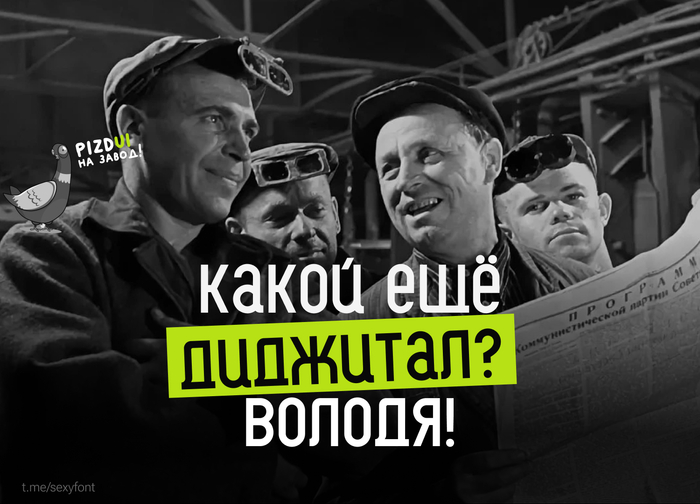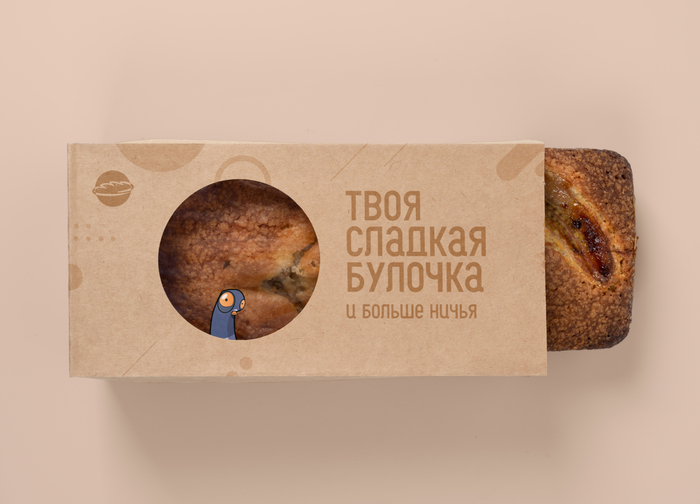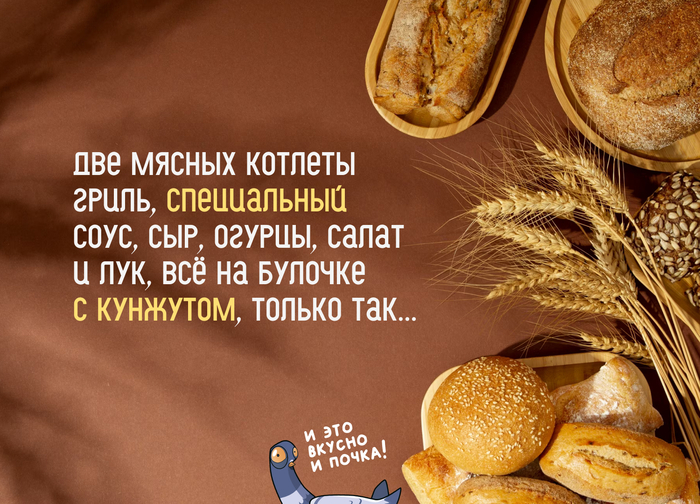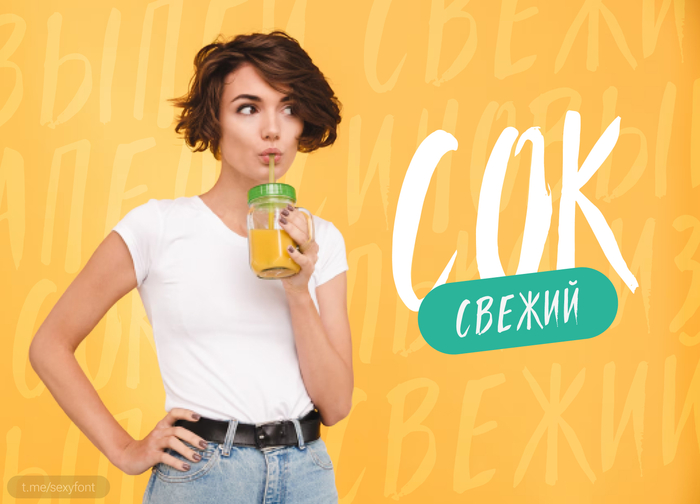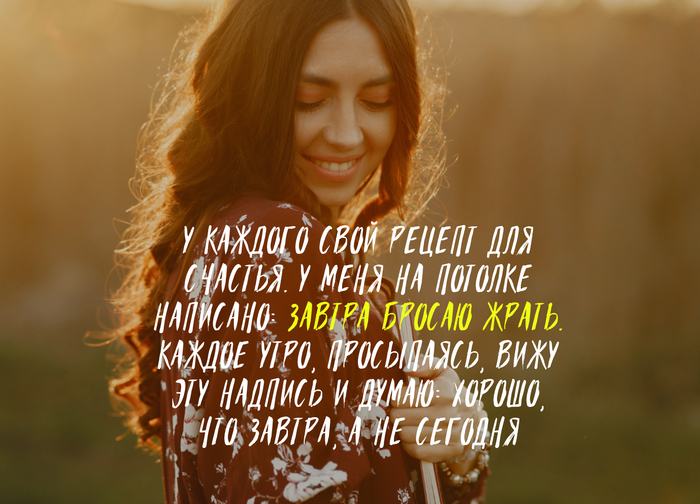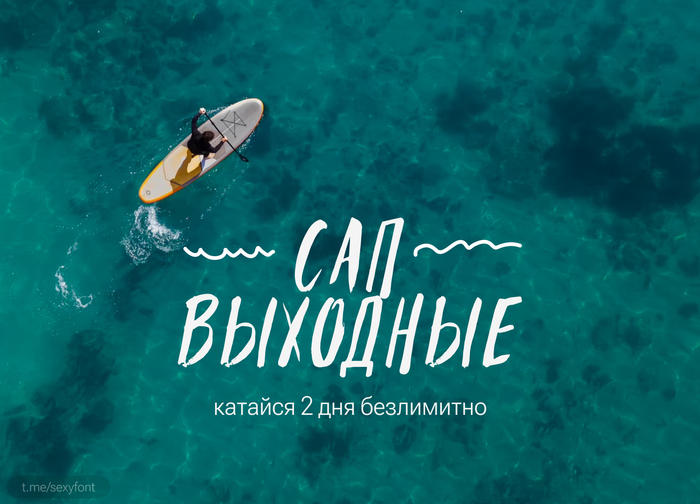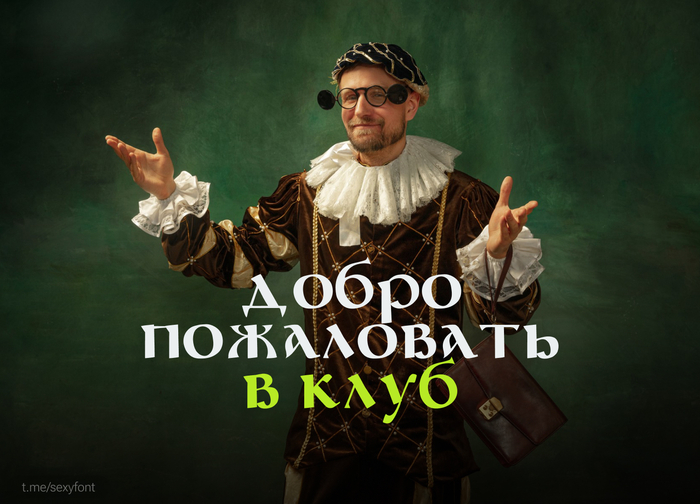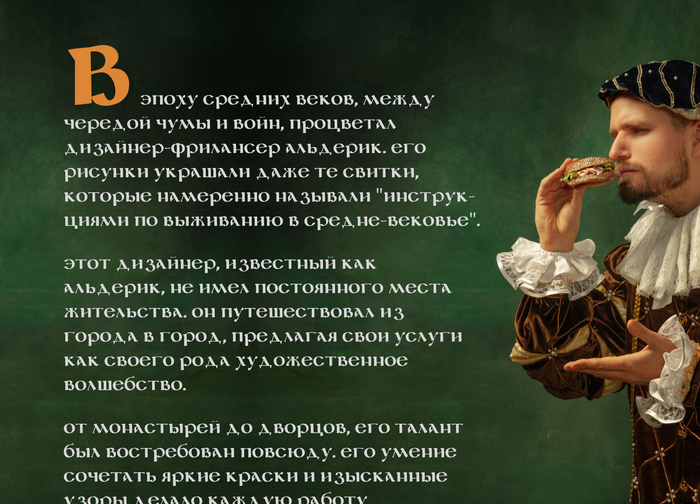
Шрифт Hlebozavod. Хлебозавод. Кириллица
Я не знаю зачем автор взял такое название. Возможно он очень любит свежие французские булочки. Ну да ладно) Главное, что это абсолютли бесплатный шрифт и конечно же с поддержкой кириллицы. Другие не публикую.
Шрифт parabola
Размашистый, рукописный шрифт parabola. Для заголовков и коротких абзацев. Бесплатно для личного и коммерции. Подобный неформальный шрифт в коллекции точно пригодится)
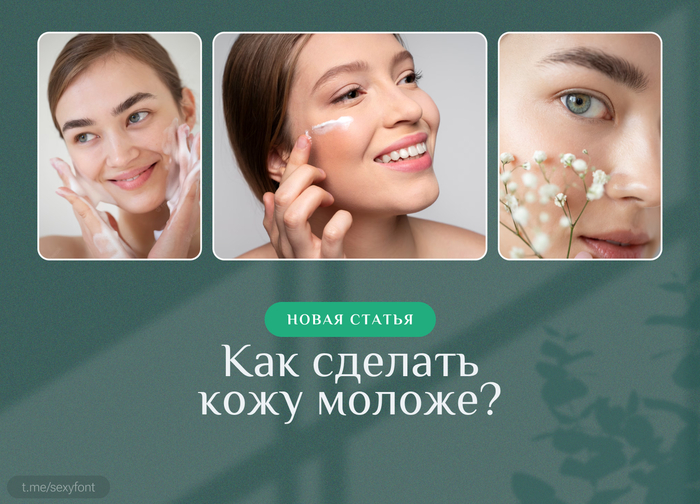
Шрифт legenda. Бесплатная кириллица
Допилил новую презентацию. Шрифт легенда. От автора: Основан на Інсулярной Мажускуле, точном церемониальном стиле письма, наиболее известным примером которого является Книга Келлса (Британия или Ирландия, ок. 800 н. э. От меня: годный шрифт под средневековые темки. Налетай, забирай)
6 шрифтов в стиле «почеркушки»
Сделал новую подборку. Эти шрифты отлично подойдут как доп. Шрифт для заметок и надписей. А так же для коротких заголовков. Под детский рисованный стиль идеально) уверен найдете им применение.
Индиана джонс тут? Adventure Indiana Jones
Динамичный, наклонный шрифт. Идеально под тематику приключений. Само название об этом кричит! Сегодня увлекся презентацией, даже фотошоп расчехлял. Люблю я походы и все, что с ними связано) Что может быть лучше проснуться в палатке и вдохнуть свежий горный воздух.
Новый халявний шрифт Marta
Шрифт может похвастаться 3мя начертаниями. Мне больше зашло наклонное, остальные слишком обычные) Бесплатный для личного и коммерческого использования.
Шрифт Philosopher
Отдохнем от декоративных шрифтов. Сегодня хороший, читаемый шрифт. Практически универсальный под любую тему. Шрифт есть в google font. За его качество можно не сомневаться) Всё в нем чики-пуки. А варианты использования я показал в презентации.